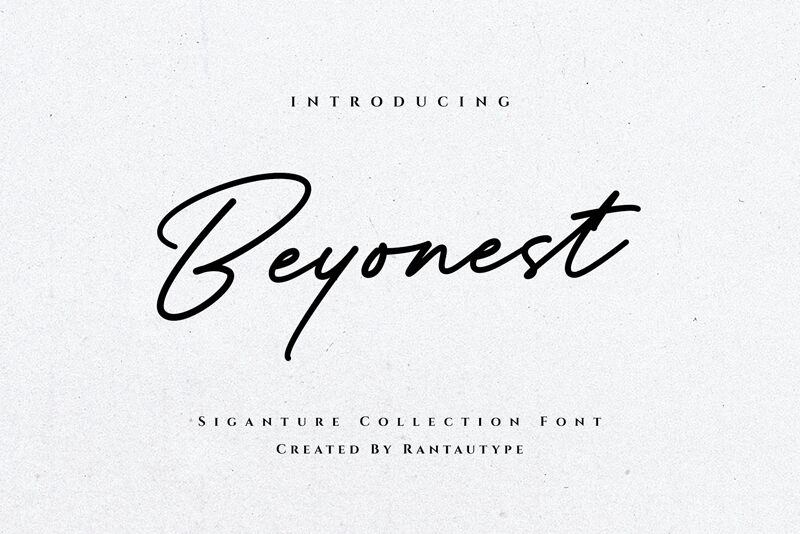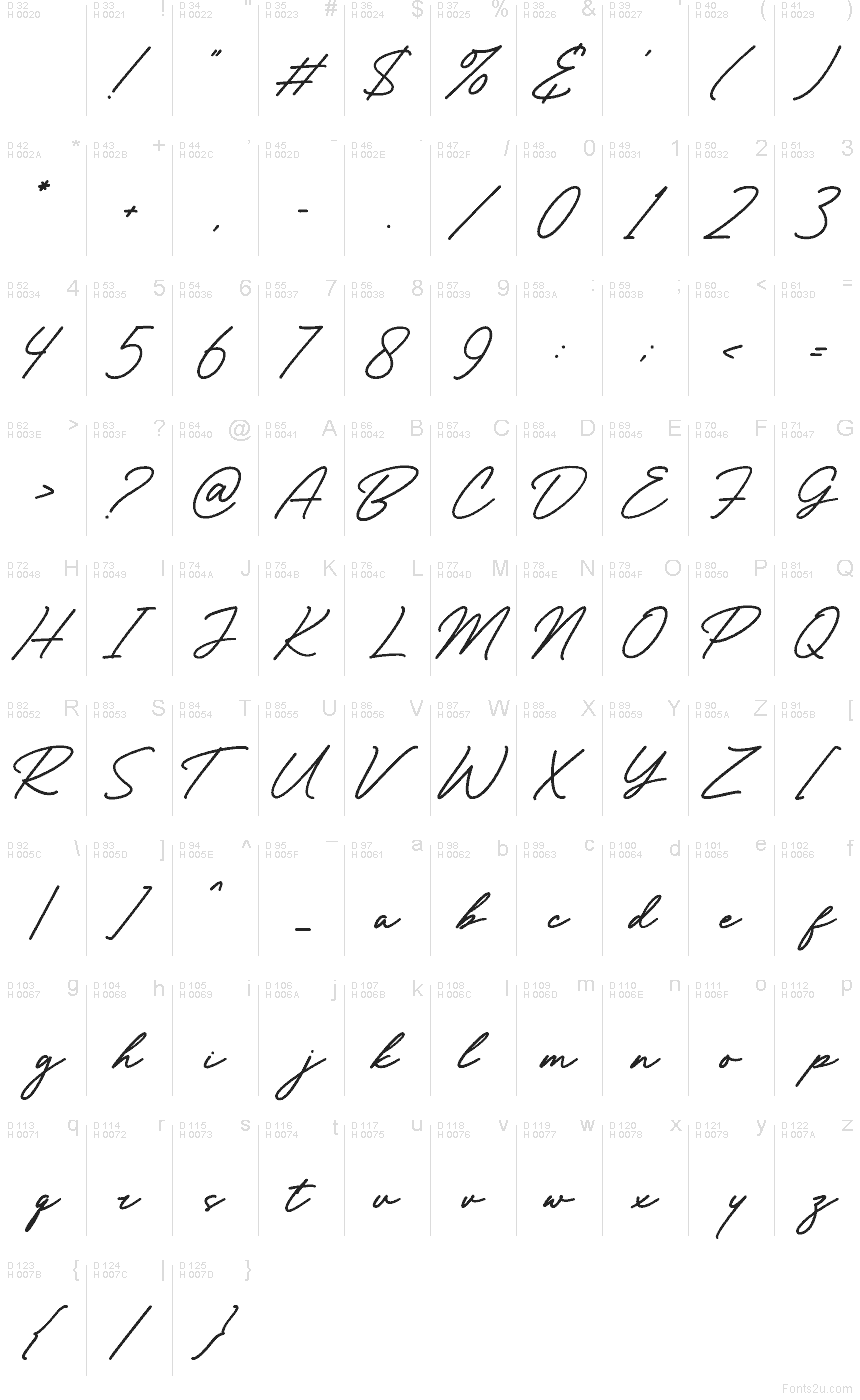
Beyonest od RantauType je bezplatné ručně psané písmo ve stylu podpisu, které zaujme svým lehce módním a vzdušným charakterem. Písmena využívají dlouhé, smyčkové tahy a jemná spojení, přičemž výrazný úvodní tah dává celému designu dojem rychlého, osobního podpisu namísto pečlivé kaligrafie.
Skvěle se hodí pro branding, obaly, grafiku na sociální sítě, pozvánky nebo nadpisy, kde potřebujete autentický vzhled rukopisu. Jako bezplatný font je Beyonest ideální volbou pro loga, titulní karty a monogramy. Díky plynulému nájezdu a přirozenému rytmu dodává krátkým slovům osobitý a bezprostřední výraz.